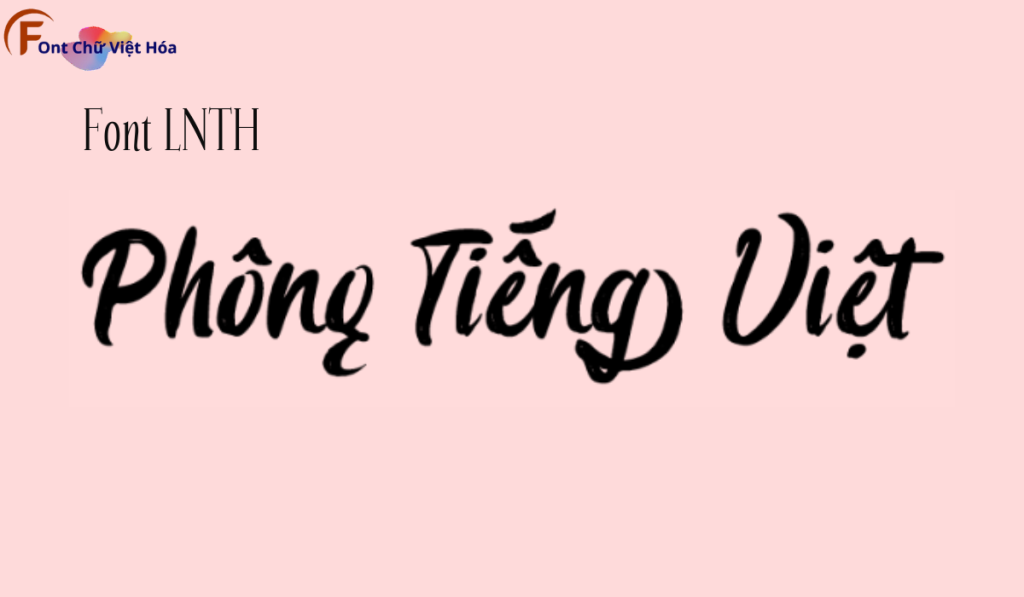
Font LNTH Cabron Việt Hóa
Tác giả: LNTH Fonts
Bộ Font: LNTH
Kiểu chữ: Sans-serif
Font LNTH Cabron Việt Hóa là một font chữ độc đáo, thuộc bộ LNTH, với thiết kế mạnh mẽ và hiện đại. Phong cách của font này phù hợp với các dự án thiết kế cần sự cá tính và táo bạo, như tiêu đề, poster, hoặc thiết kế đồ họa. Font LNTH Cabron Việt Hóa mang đến sự mạnh mẽ và dễ nhận diện, ứng dụng trong các lĩnh vực sáng tạo. Đặc điểm hình dạng của font bao gồm các đường nét dày và sắc sảo, giúp tăng tính thẩm mỹ và sự chú ý. Việc Việt hóa font giúp người dùng dễ dàng sử dụng trong các thiết kế tiếng Việt, mang lại sự tiện lợi và linh hoạt.